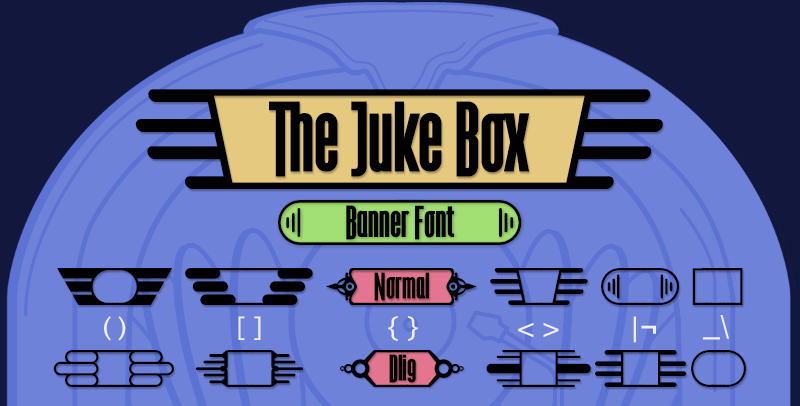
A The Juke Box Font é uma tipografia sans-serif que se inscreve num retângulo, criando uma atmosfera vibrante e animada. Este design minimalista não apenas oferece uma aparência agradável para seu texto, mas também uma sensação de movimento e energia com sua disposição em formato rectangular. Como designer, defharo conseguiu criar um conceito único que se assemelha à experiência dos boxes na música ao vivo, sendo perfeitamente adaptado para o ambiente digital atual onde tanto a música quanto o design são sempre vivos e ativos. A fonte é ideal para aplicações web e redes sociais, adicionando uma pitada de vida e energia que seu conteúdo merece. Com 12 setas diferentes do tipo JukeBox no final da fonte, você pode variar a forma em que seu texto se desenvolve ao longo do retângulo, criando um visual dinâmico que cativa o olhar e mantém o interesse constante.